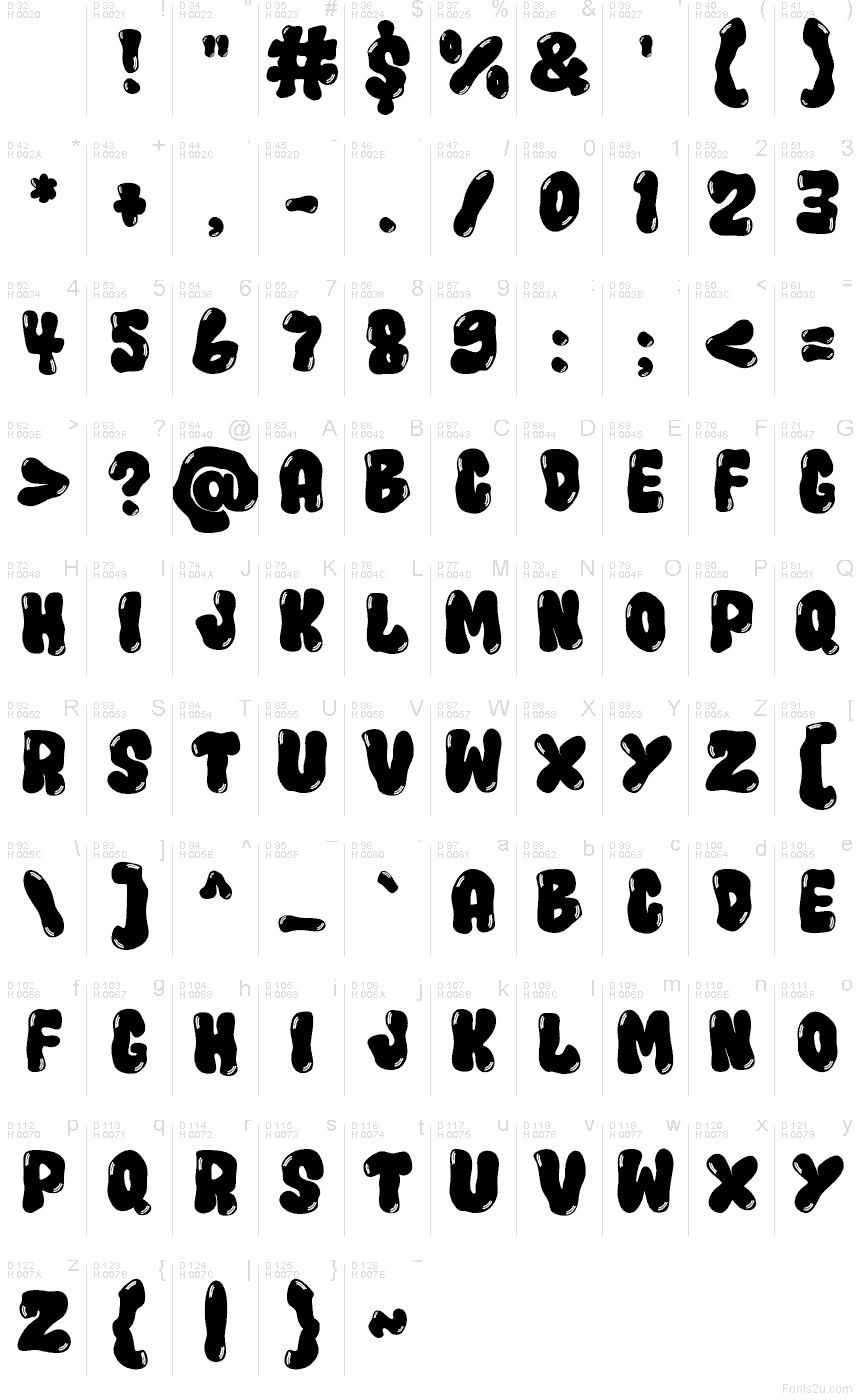
Chunk Wave Deco
Chunk Wave Deco, firmato Rizal Yusepudin Salman & Muhammad Panji Ramdhani di Cikareotype x Figuree, è un font groovy gratuito che colpisce come un urlo dai bordi morbidi. Le sue forme tozze e rigonfie sono quasi soffici: tratti neri audaci con intagli ondulati che aggiungono rimbalzo e un ritmo giocoso. È rumoroso senza essere disordinato, mantenendo una fluidità spavalda e divertente anche nei grandi formati.
Usa Chunk Wave Deco per dare carattere immediato a titoli di poster, copertine di album, grafiche streetwear, volantini per festival, packaging retro, promozioni social e adesivi incisivi. Questo font gratuito brilla nelle frasi brevi e nelle parole grandi dove l'oscillazione può respirare; usa un tracking generoso e ampi margini. Abbinalo a una sans serif geometrica pulita (o una semplice grotesk) per il testo principale, così da mantenere l'energia ben concentrata.